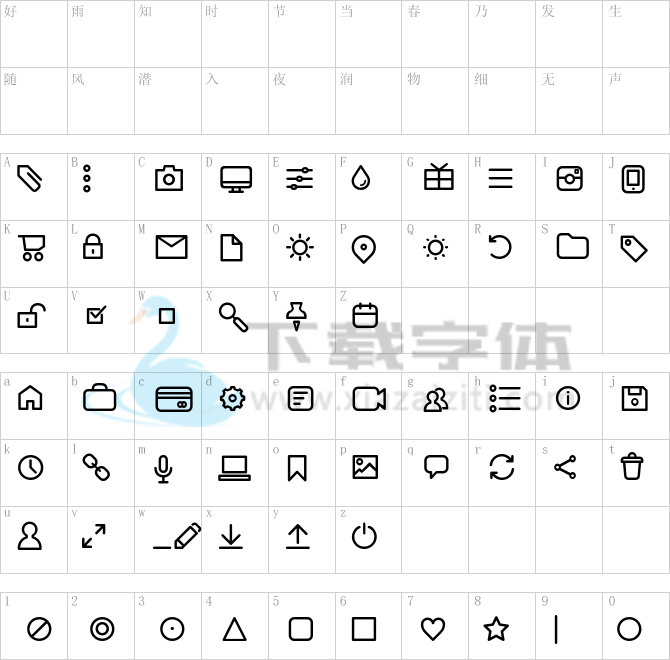
Arista Pro Icons Light.ttf字体下载,这款字体结构工整、笔画清晰,兼顾美观与易读性,适用于标题、正文、海报、包装、LOGO 等多种场景。字形优雅稳定,风格百搭耐看,适配日常排版与创意设计,让文字呈现更舒适、更具质感。Arista Pro Icons Light.ttf字体下载一笔一画,皆是细节,以均衡的比例、流畅的线条打造舒适视觉体验,字形端正大气,风格简约现代。无论是商业设计、品牌宣传还是日常排版,都能轻松驾驭,让文字更有格调与力量。Arista Pro Icons Light.ttf字体下载字体下载。